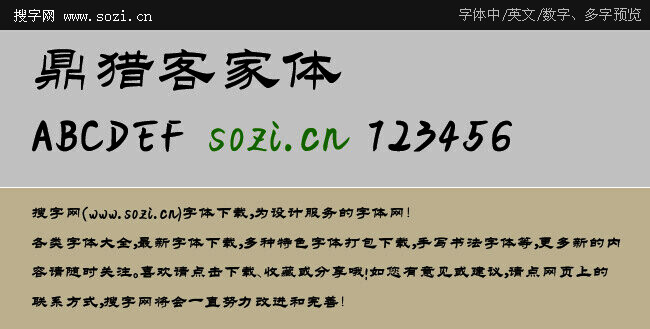
鼎獵客家體
搜字網提供一款鼎獵客家體中文藝術字體下載,鼎獵客家體以富有中國文化底蘊距今1600年魏晉南北朝時期社會流行字體爨體字體為參照,爨體字所具有的古韻、渾厚、拙樸特質,與客家文化相互交融。由此碰撞出專屬于客家人的鼎獵客家體。是一套根據簡體中文漢字編碼國家標準(GB2312編碼)設計的字體,并在此基礎上一共設計了6789個簡體漢字。字體適合海報設計、廣告創意、包裝設計等應用。